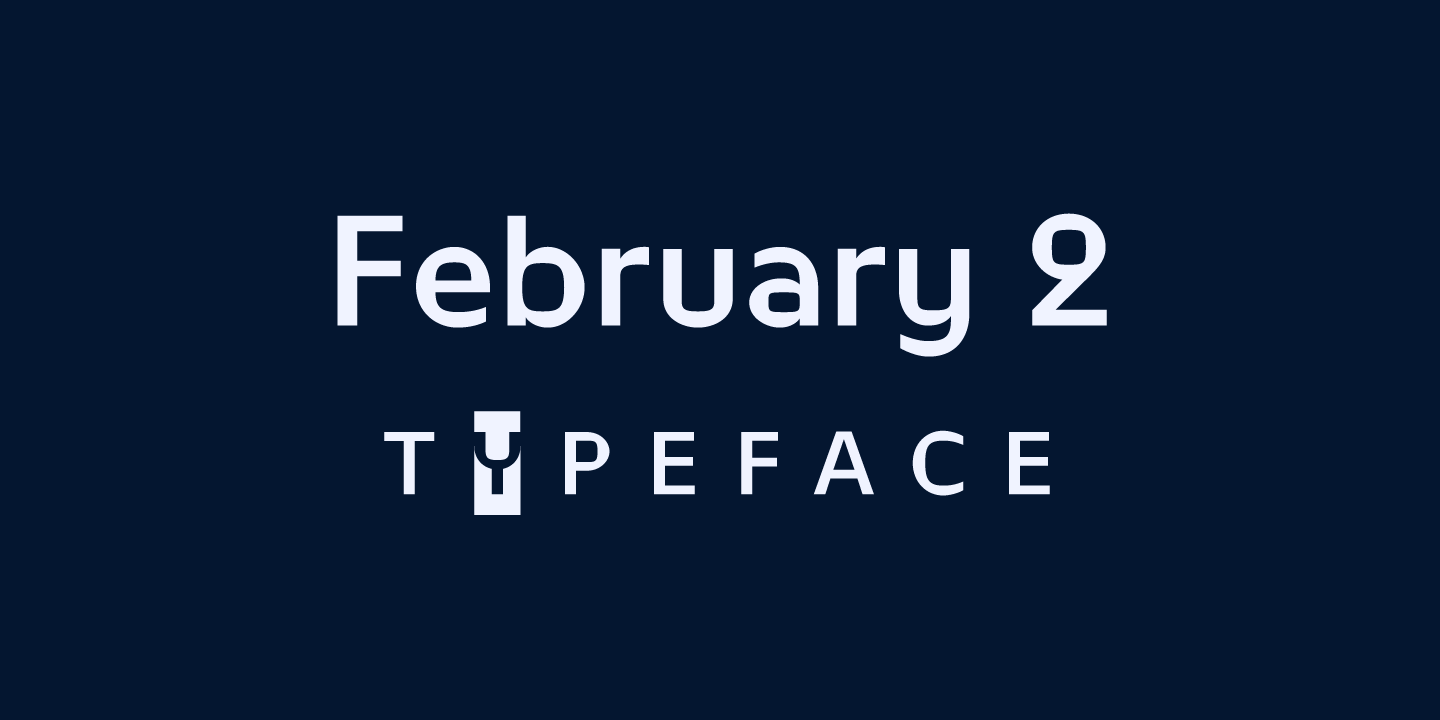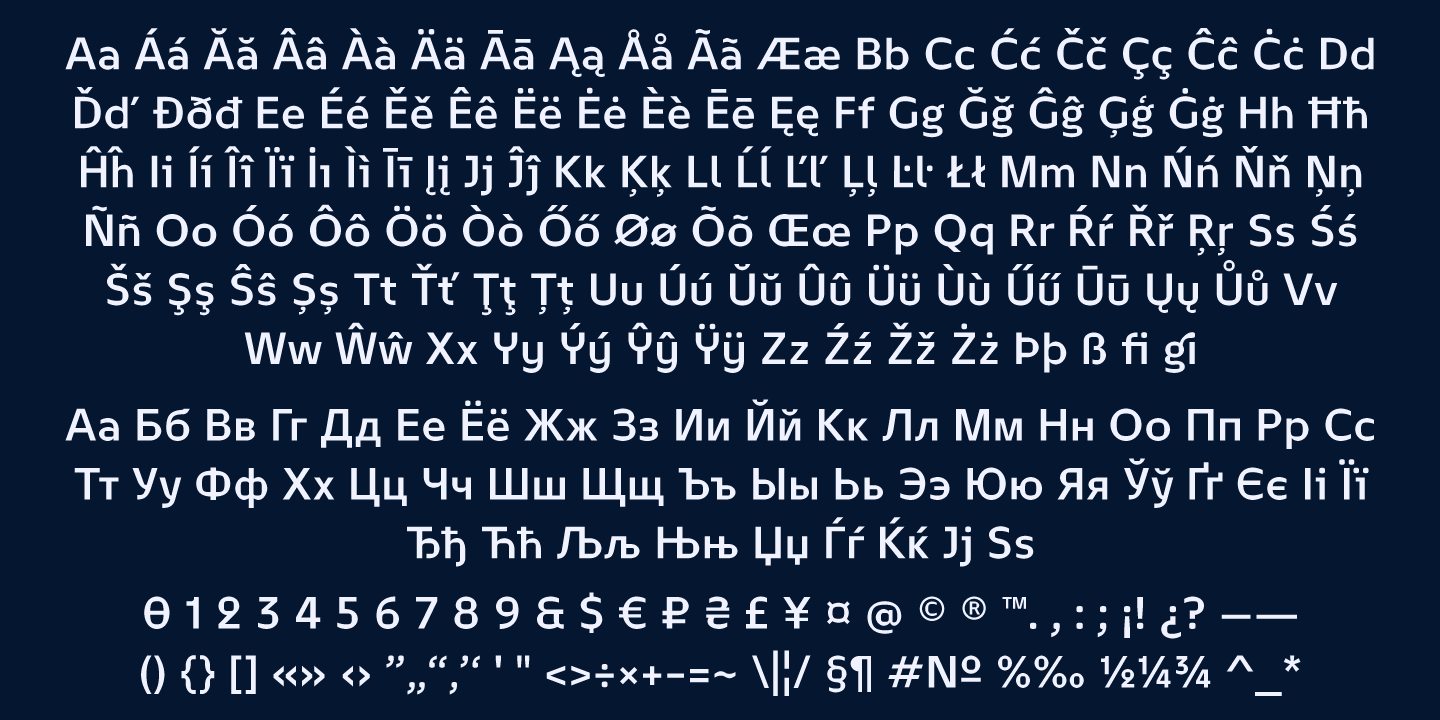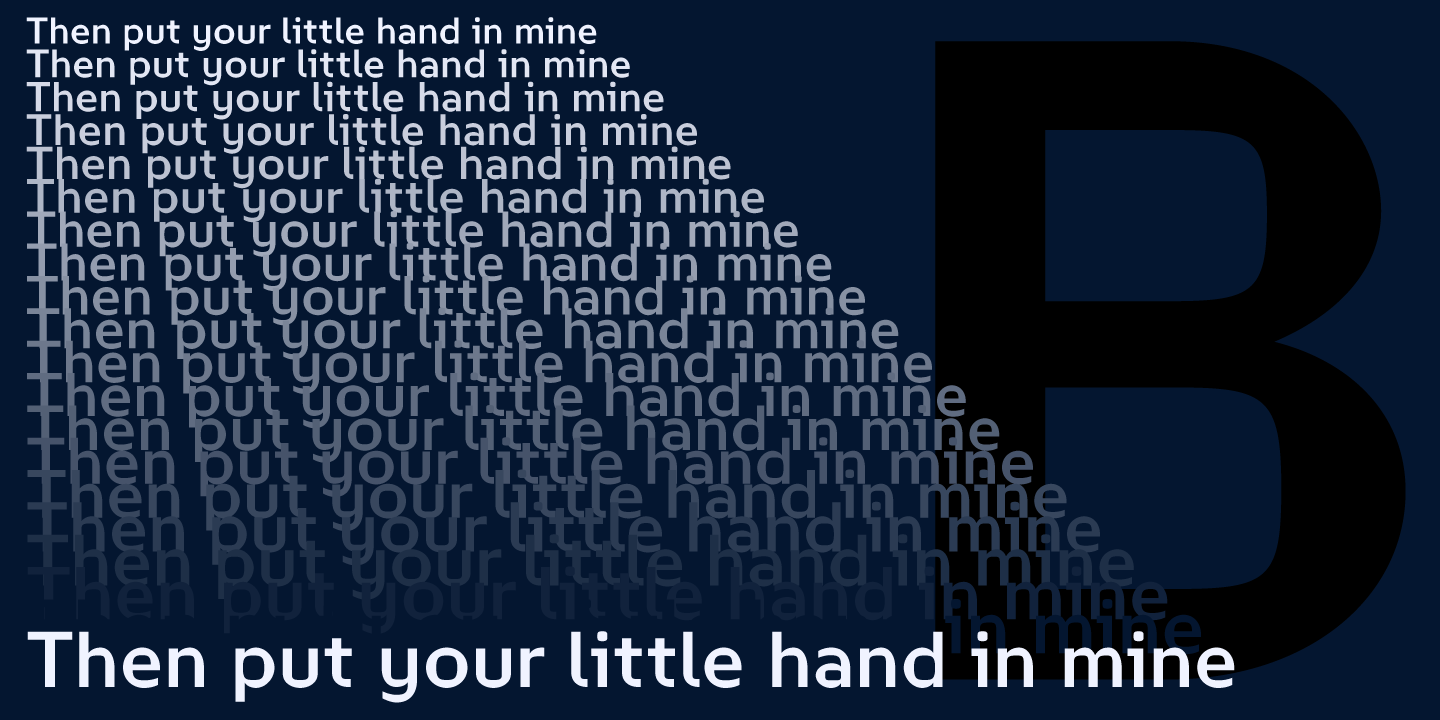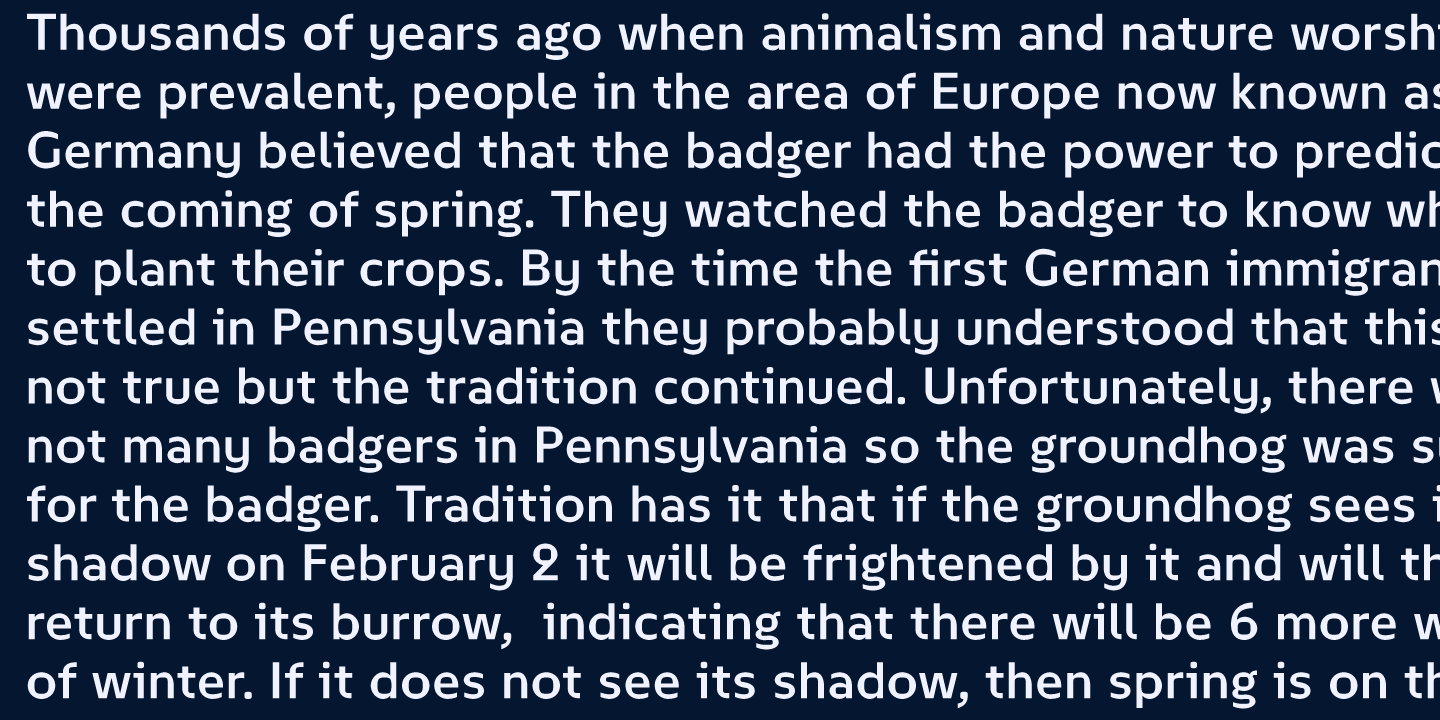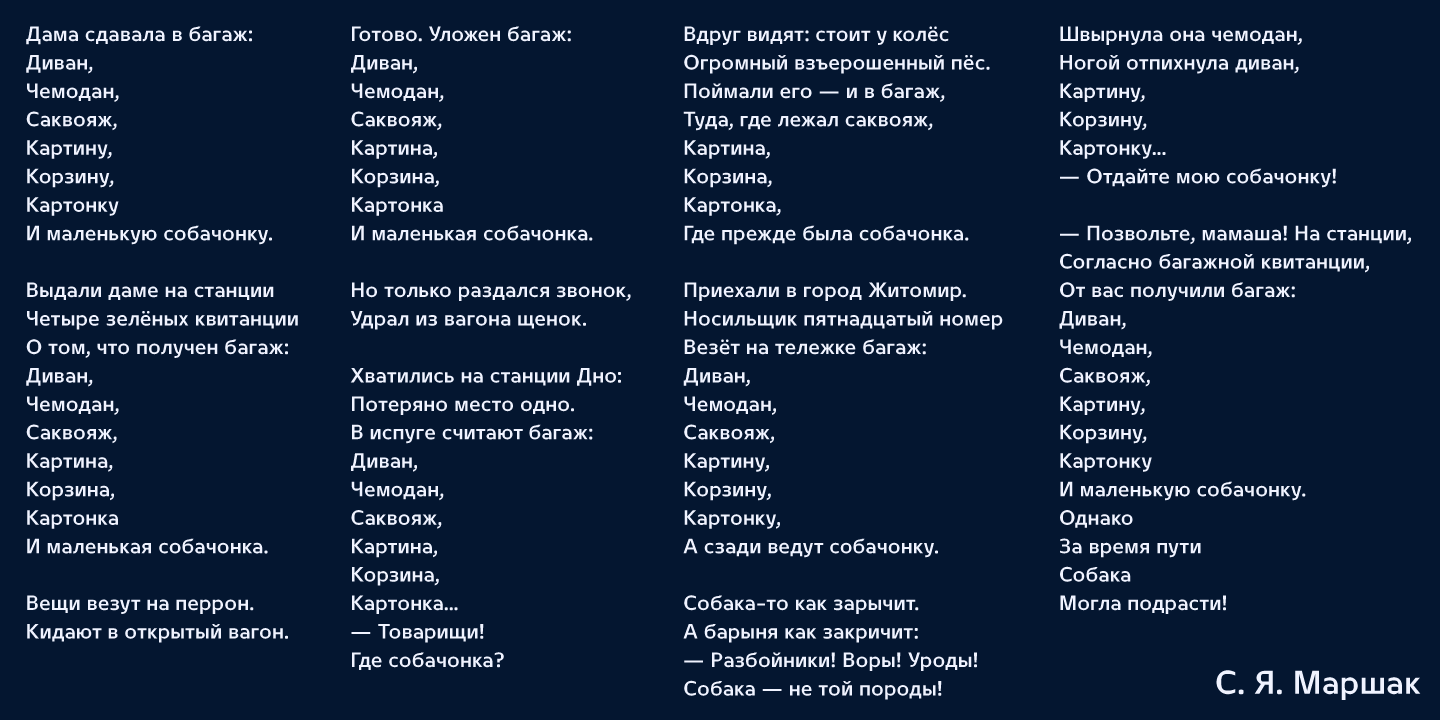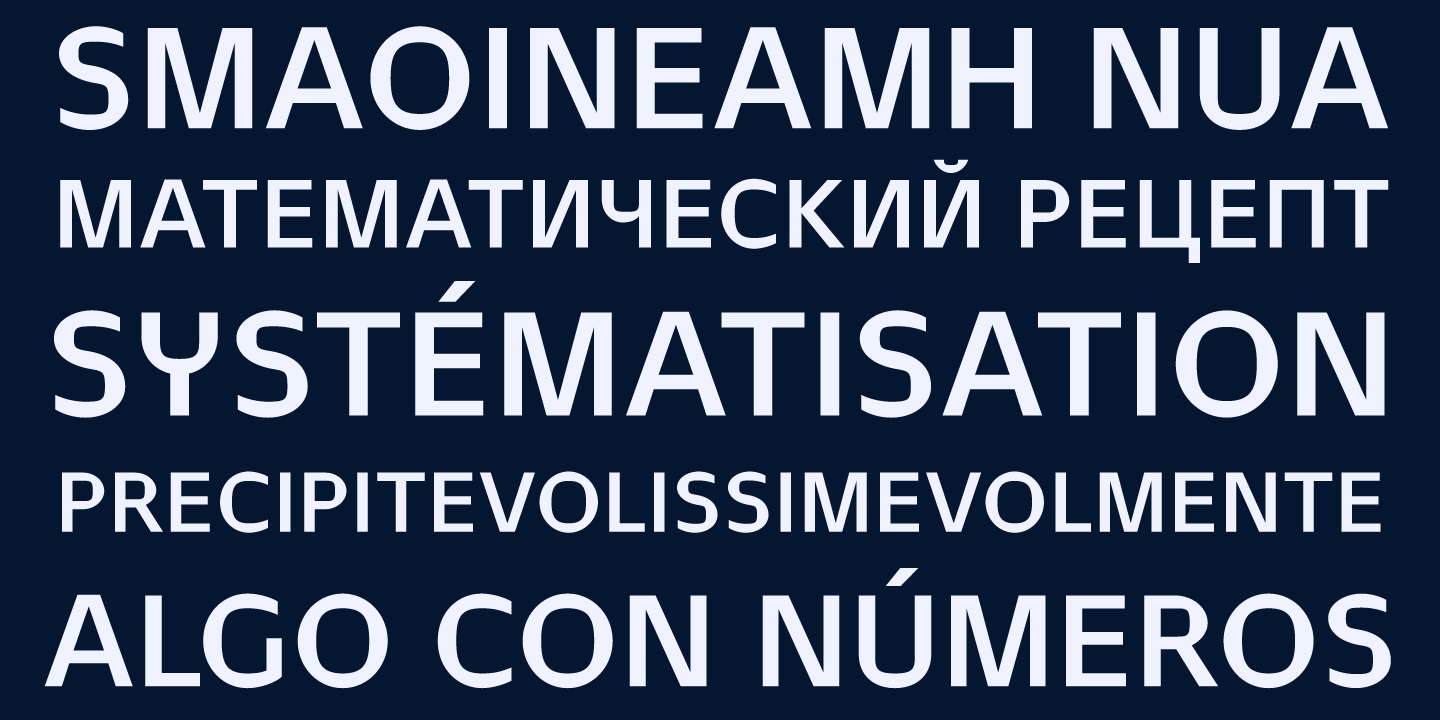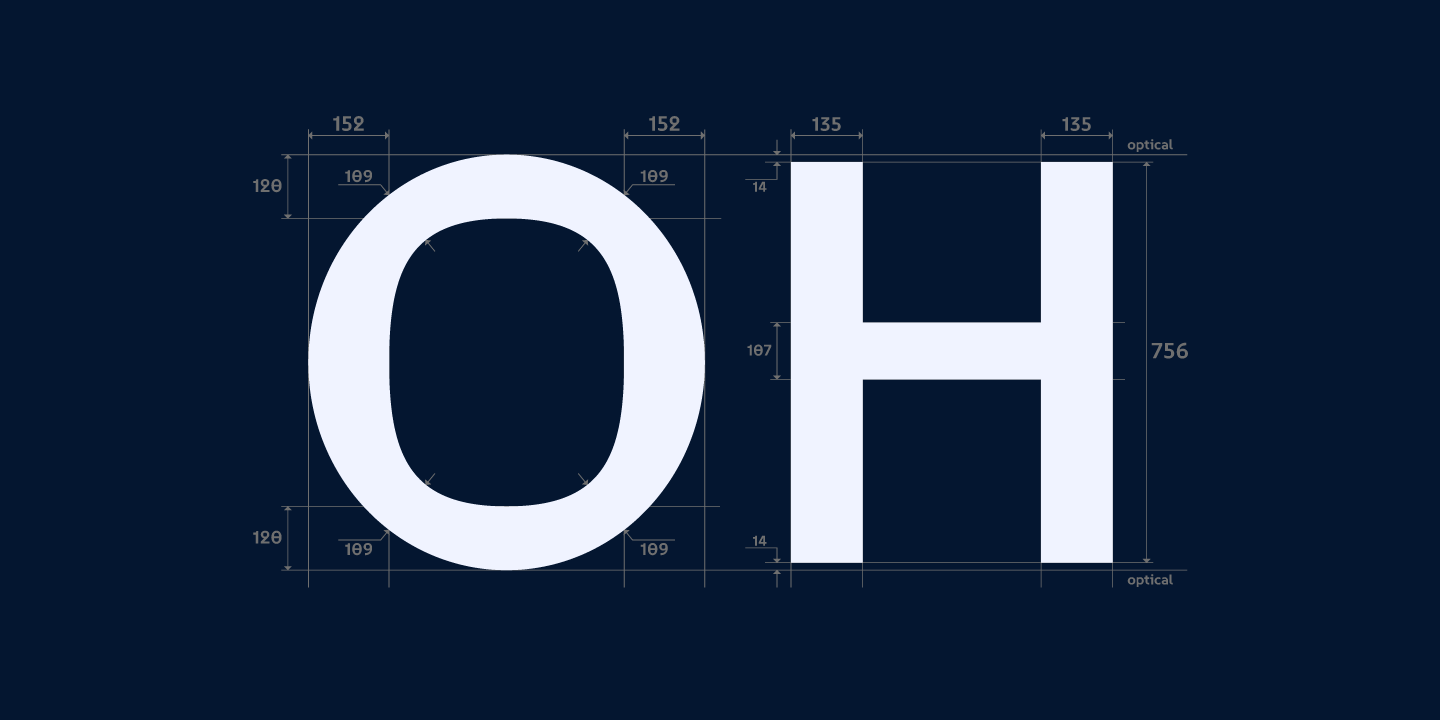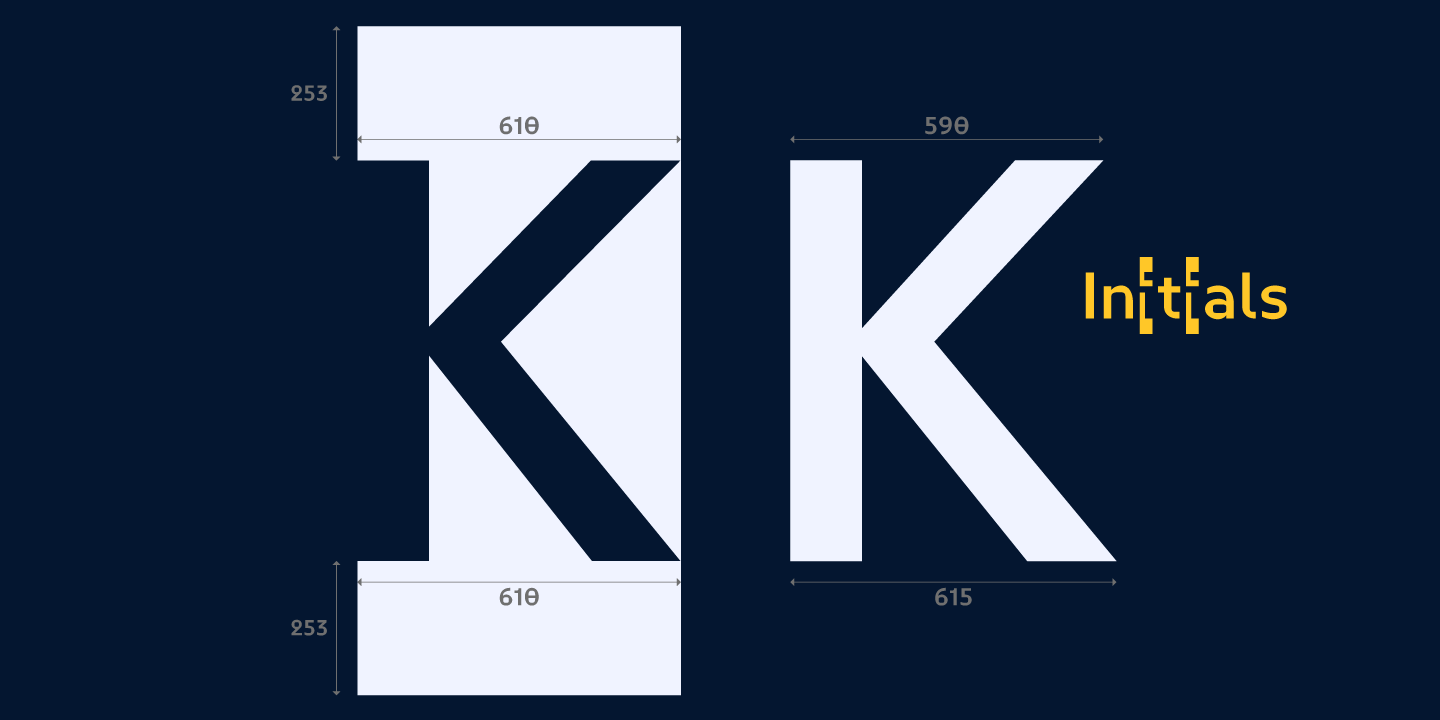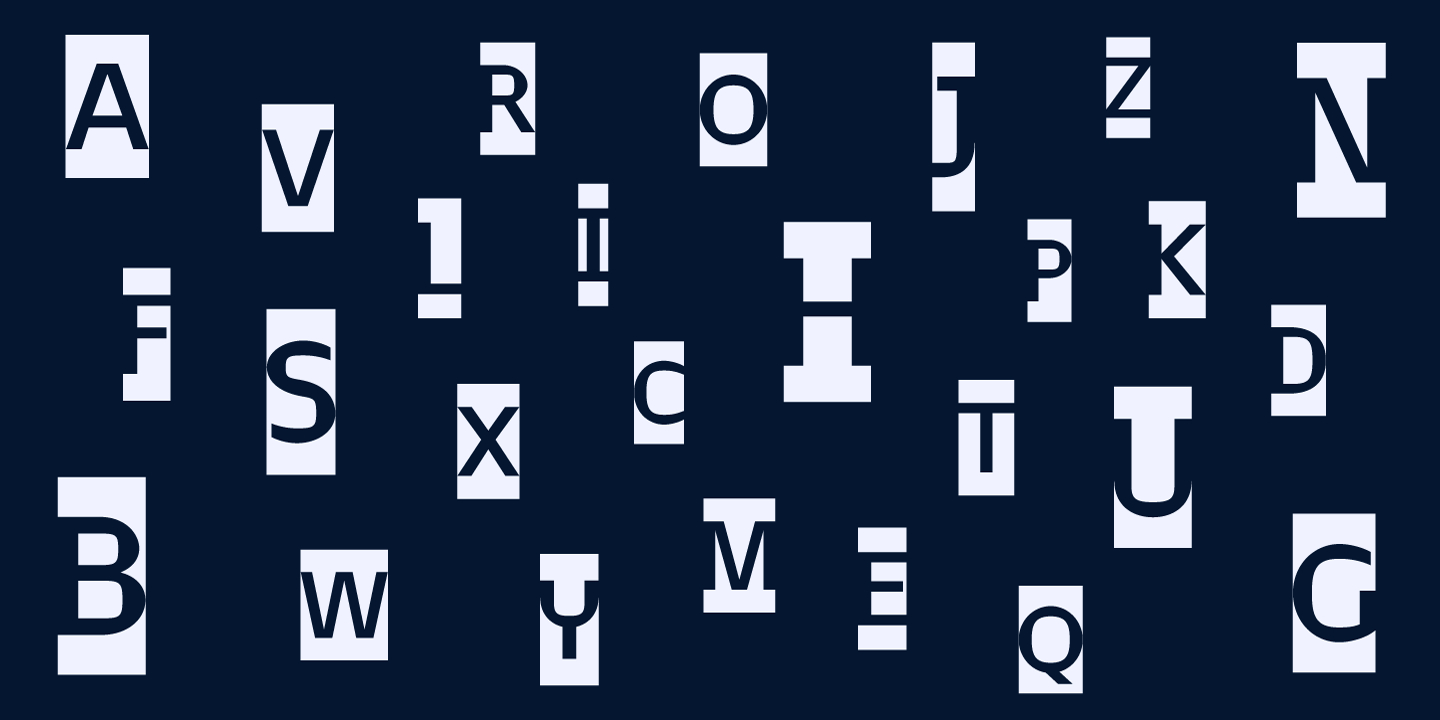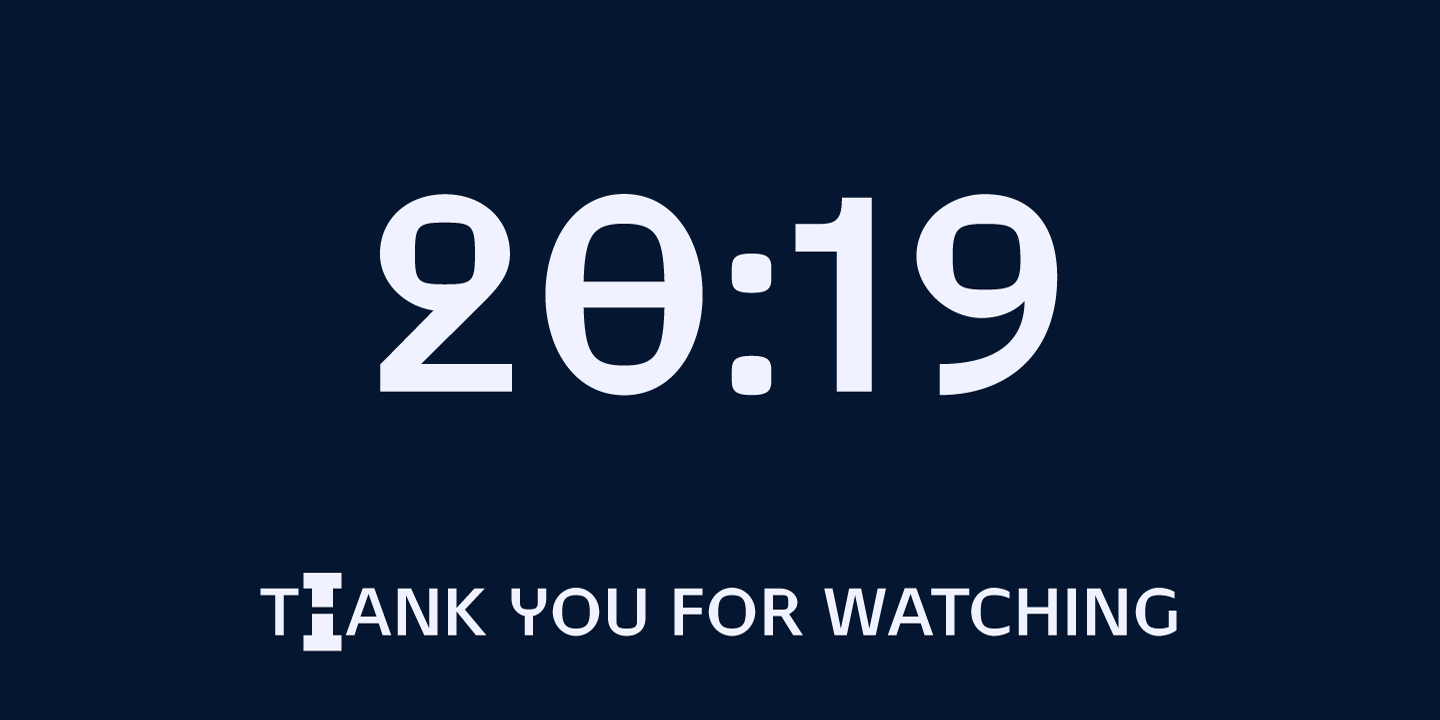
February 2 | font
Шрифт второе февраля разработан по экспериментальному принципу построения гротесков, сочетающий в себе контраст между овалом и скругленным прямоугольником. Шрифт выпущен двумя стилями - для обычного текста и инициалов. Каждый стиль содержит более 400 глифов, поддерживает кириллицу и расширенную латиницу.
Разработан в 2019 году.
Шрифтовой дизайнер Игорь Косинский